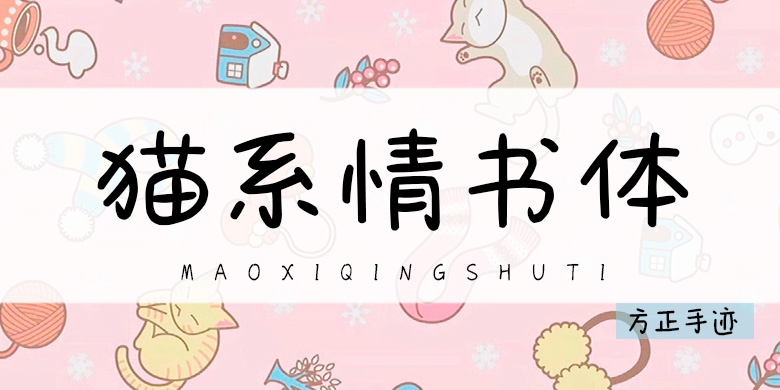
方正手迹-猫系情书体
方正手迹-猫系情书体,这款字体结构工整、笔画清晰,兼顾美观与易读性,适用于标题、正文、海报、包装、LOGO 等多种场景。字形优雅稳定,风格百搭耐看,适配日常排版与创意设计,让文字呈现更舒适、更具质感。方正手迹-猫系情书体一笔一画,皆是细节,以均衡的比例、流畅的线条打造舒适视觉体验,字形端正大气,风格简约现代。无论是商业设计、品牌宣传还是日常排版,都能轻松驾驭,让文字更有格调与力量。方正手迹-猫系情书体字体下载。
猫系情书体是一款可爱风格的圆体字,字体笔画简洁,字形整体偏扁,加上一些古灵精怪的笔画显得俏皮可爱而又爱意满满。适用于文艺、卡通、漫画类的书刊、品牌广告和产品包装设计,以及社交网络的个性化用字。